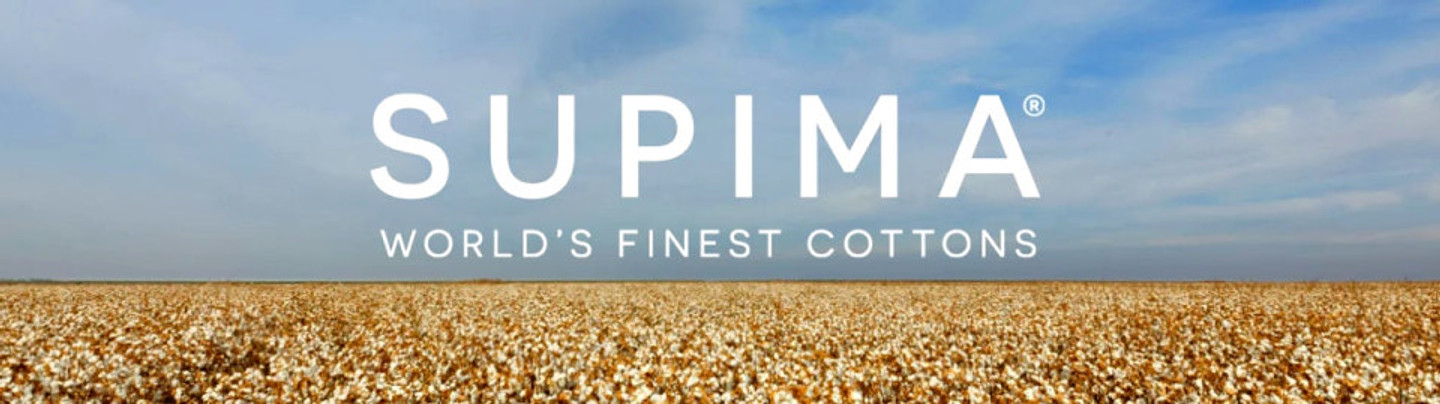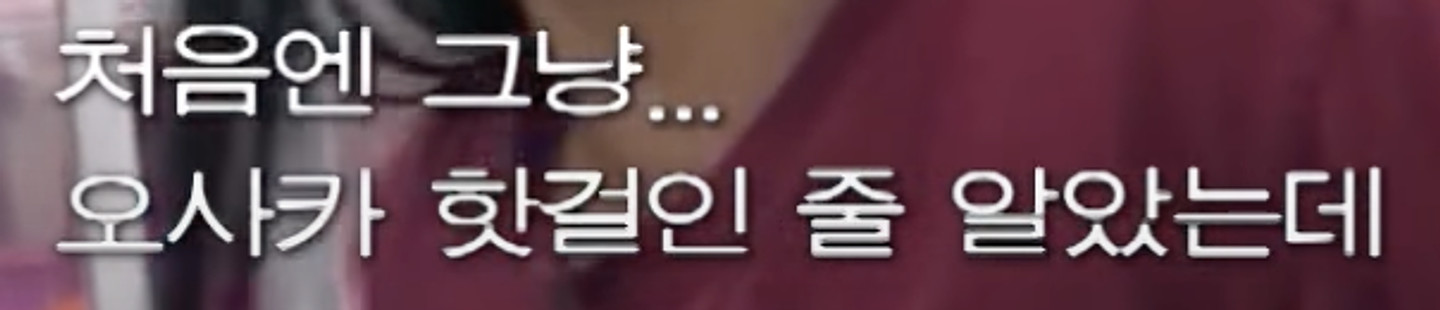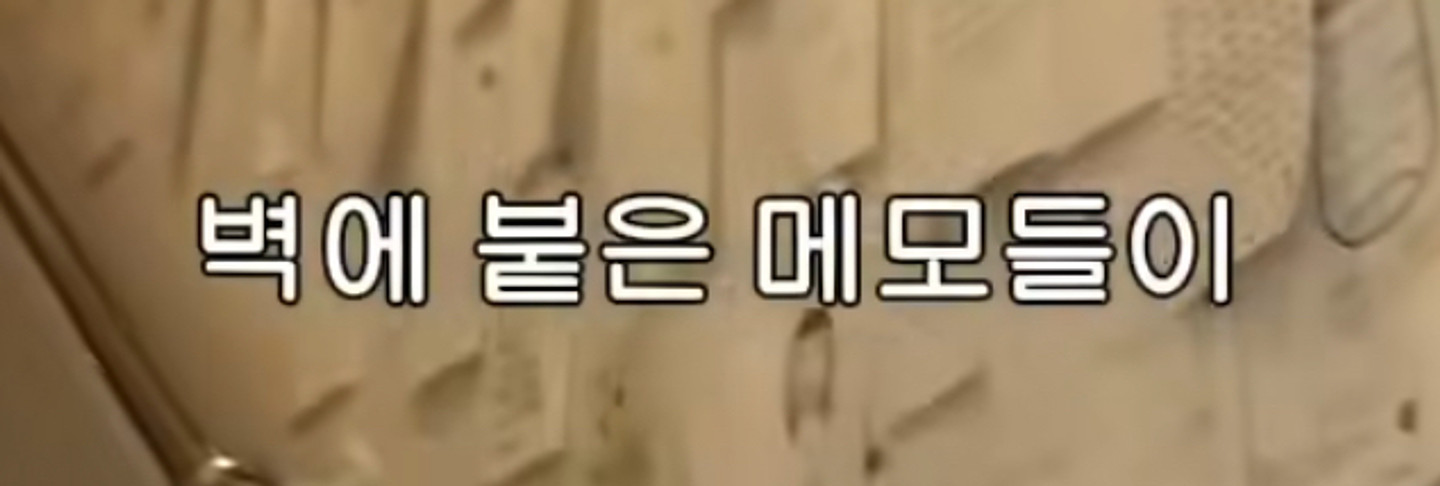
가운데폰트 뭔가요 진짜급함
무슨 폰트인지 아시나요?ㅠㅠ
이 폰트 이름 궁금해요 !
여기서 한글 폰트 뭘까요?
깔려있는 고딕을 다 찾았는데 똑같은게 없네요 똑같이 해달라고 하는데 이 폰트 아시는분 계실까요?
타이틀로 사용된 폰트가 무엇일까요?
고딕하면서 볼드한 체야
오십프로 트레일러에서 본 폰트인데 무슨 폰트인지 알 수 있을까요?
무슨체 일까요? 문의드립니다.
이거 폰트 뭘까요..??.? 넘 궁금해요ㅜㅜ!! 도와주세요ㅎㅎ
어떤 폰트인지 알려주세요
삼호 글자에 쓰인 폰트가 어떤걸까요?
산돌폰트 말고 비슷한 무료폰트 있을까요?
이폰트 알수있을가요???
한글과 아래 영어랑 숫자 모두 궁금해요ㅠㅠ
규진님 유튜브 영상인데 장소 폰트 알 수 있을까요 ㅜㅜ ??
일러스트가 졸귀 폰트 알 수 있을까요 ㅜㅜ ??
잘모르겠어요
이 폰트 무슨 폰트인지 아실까요??ㅠㅠ
혹 이폰트 무슨폰트일까요?
무슨 폰트인지 궁긍합니다
이거 무슨 폰트인가요ㅠㅠㅠㅠ?? 고딕계열이라기엔 살짝씩 휘어있어요
폰트 알려주세요!!
이거 무슨 폰트인지 알려주세요 ㅠㅠ
진하게 설정한걸까요? 무슨 폰트일까요
어떤 폰트인가요?!
이 폰트를 저희 밴드 굿즈에 넣고 싶은데ㅜ 사용 가능 한지 여쭙고 싶습니다, 어떤 폰트인지도요!
무슨 폰트인가요!!
무슨 폰트인가요?!
동물의 숲 폰트 뭐인가요!!!
이 폰트 궁금해요.
이 폰트 제발 알려주세요..
이 폰트 아시는 분 !
폰트 몰까요,,??
부산 시내버스에 쓰이는 숫자인데... 폰트 아시는 분 있을까요..? 숫자 가운데 선은 없어도 돼요..
폰트 뭔지 알 수 있을까요?
이 글씨체는 뭘까요??
이건 무슨 글씨체일까요?
간판에 쓰인 폰트를 찾을 수 있을까요? 저 텍스트를 사용해 작업을 하려고 하는데 간판한지가 오래 되어서 정보가 남은게 없네요 ㅠㅜ
이 폰트 뭔지 궁금해여ㅜ!
이 폰트 궁금해요ㅠ
이 폰트 궁금해용!!!
이 폰트 뭘까요?ㅠㅠ
영문서체는 봐도 봐도 헷갈리네요 폰트명 아시는 고수님 계실까요?
지무비에서 사용하는 약간 공포스러운 분위기의 글씨체가 궁금합니다
폰트랑 뒤에는 그림자 설정한걸까요?
무슨폰트일까요?ㅠ
무슨폰트인가요!!
캘리그라피는 아닌거 같고 몇년전 글자체인듯